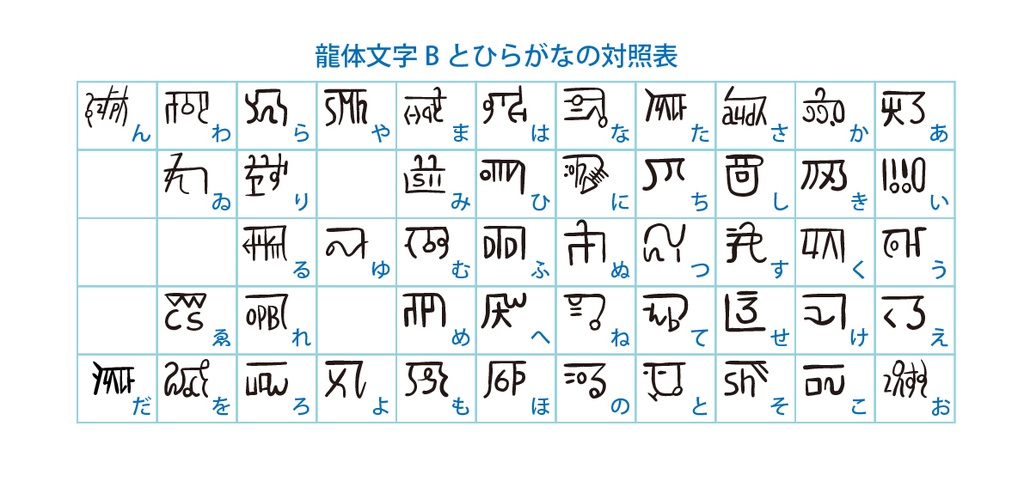
龍体文字の手書き風フォントです。 龍体文字Aと比べ、なるべく正方形に近い字形にしています。 龍体文字とは神代文字の中でも最も古く5600年前に作られたと言われる文字。48字ある文字それぞれにパワーが宿っているとされています。 ひらがな48文字(ゐゑ含む)に対応した龍体文字があるので、ひらがなを入力すると相当する龍体文字が表示されるようにしました。 フォントファイルの形式はOpenTypeファイルです。 MacOS VenturaとWindows11での動作確認はしています。 【収録文字】 ひらがな(あいうえおかきくけこさしすせそたちつてとなにぬねのはひふへほまみむめもやゆよらりるれろわゐゑをん) ※濁音、半濁音、拗音、促音はありません。 【データ内容・使用方法】 zipファイルを解凍してください。 OpenTypeファイル pkryutaib3-Regular.otf JPGファイル(龍体文字とひらがなの対照表) comparison.jpg テキストファイル readme.txt が収録されています。 pkryutaib3-Regular.otfをインストールしてください。 【購入の際の注意点】 商用利用OKです。 使用した場合、ご一報いただけるとうれしいです。Twitterなどで紹介します。 フォントファイルの改変・再配布は禁止です。 ※2024.2.4追記 スペースが■に変換されていたのでファイルを修正しました。 ※2024.6.18追記 「た」の龍体文字の書き方には2とおりあるようなので、異体字を「だ」に収録しました。